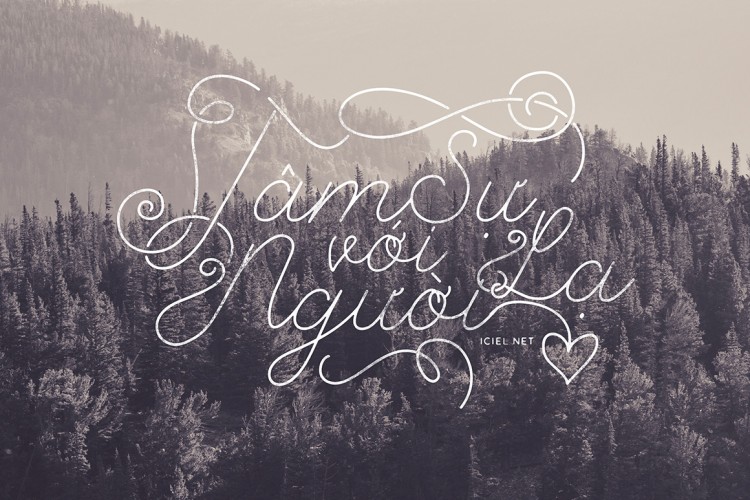
Giới thiệu về Font việt hoá iCiel Humble Hearts
Trong thế giới thiết kế đồ họa, việc lựa chọn một Font Chữ phù hợp đóng vai trò quyết định đến cảm xúc của người xem. Font việt hoá iCiel Humble Hearts là một trong những bộ phông chữ thuộc phong cách Script (viết tay) được yêu thích nhất hiện nay. Với những đường nét mềm mại, uyển chuyển và mang đậm tính nghệ thuật, bộ font này mang đến vẻ đẹp vừa chân thực vừa gần gũi. Điểm đặc biệt của phiên bản iCiel là đã được tối ưu hóa đầy đủ dấu tiếng Việt, giúp các bạn học sinh và giáo viên dễ dàng sử dụng trong học tập cũng như trình bày văn bản.
Tại sao nên sử dụng iCiel Humble Hearts?
Bộ Font việt hoá iCiel Humble Hearts sở hữu hệ thống ký tự đa dạng với các đường nối chữ tinh tế. Điều này giúp văn bản trông giống như được viết tay một cách cẩn thận và nắn nót. Phông chữ này rất phù hợp cho các thiết kế thiệp mời, bìa sách, nhãn vở hay các bài thuyết trình cần sự sáng tạo và tính cá nhân hóa cao. Đối với các bạn học sinh, đây là lựa chọn tuyệt vời để làm nổi bật các tiêu đề bài học, tạo nên sự hứng thú trong quá trình ghi chép và học tập mỗi ngày.
Cách ứng dụng Font việt hoá iCiel Humble Hearts hiệu quả
Để phát huy tối đa vẻ đẹp của Font việt hoá iCiel Humble Hearts, bạn nên kết hợp nó với các font chữ không chân (Sans-serif) đơn giản cho phần nội dung chi tiết. Sự tương phản này sẽ giúp tiêu đề trở nên nổi bật và dễ đọc hơn. Ngoài ra, việc sử dụng các tông màu pastel nhẹ nhàng sẽ càng tôn lên nét lãng mạn và ngọt ngào của bộ font. Hy vọng rằng bộ font này sẽ trở thành công cụ đắc lực giúp bạn tạo ra những sản phẩm thiết kế ấn tượng và đầy cảm hứng. Hãy tải ngay Font Miễn Phí, Font Việt Hóa, Font việt hoá iCiel Humble Hearts để bắt đầu sáng tạo nhé.